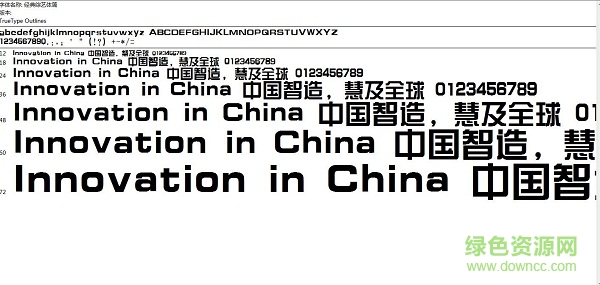
1.無襯線體加粗筆畫的話,更適合變化為剛勁有力的字體,尤其是在漢字中, 這類字體氣勢突出,視覺沖擊力明顯,個性張揚(yáng)有力,節(jié)奏分明,可以用于變現(xiàn)強(qiáng)烈的信心和勇氣,表現(xiàn)凝聚力和號召力,給人視覺上的震撼。
2.無襯線體筆畫變細(xì),或者邊角變?yōu)榛⌒蝄圓角時,又給人以柔美、纖細(xì)、溫和、飄逸等感覺,適合表現(xiàn)情感類設(shè)計主題、女性設(shè)計主題、公益類設(shè)計主題等等。